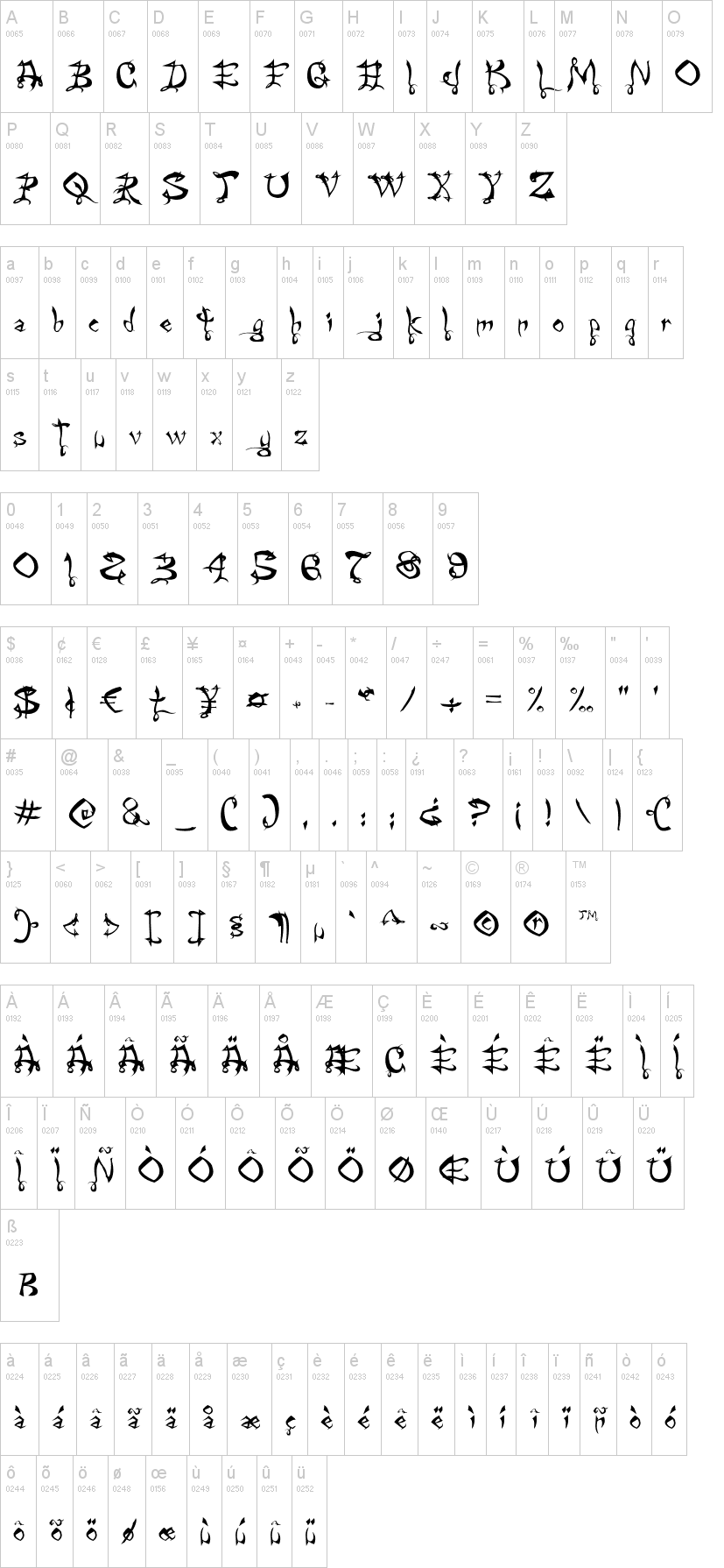
Note of the authorFAELOREHN NOVELLA FONT:
Dalla scrittrice Jenna Elizabeth Johnson, autrice del fantastico mondo di OESCIENNE, una inedita trilogia (completata con gli esclusivi due ultimi capitoli del mondo parallelo esplorato dalla giovane Meghan) devoluta nel nome di FAELOREHN. Atmosfere soft dark per un intimista viaggio nellinconscio di una ragazza che esplora i propri sentieri dellanima, alla ricerca del segreto dellAmore.
By writer Jenna Elizabeth Johnson, author of the fantastic world of OESCIENNE, an unprecedented trilogy (completed with exclusive last two chapters of the parallel world explored by young Meghan) donated in the name of FAELOREHN. Dark atmospheres for an intimate journey into the unconscious of a girl who explores their paths of the soul, in search of the secret of Love.